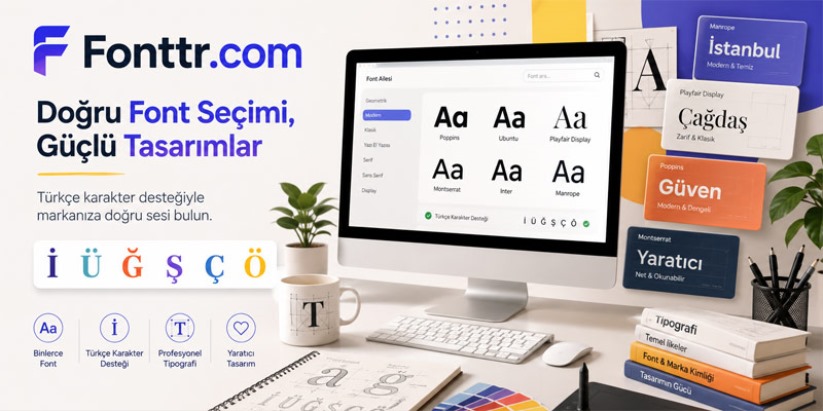
Dijital tasarımda kullanılan yazı tipi, bir görselin ya da web sayfasının ilk bakışta nasıl algılanacağını doğrudan etkiler.
Bir başlığın güçlü görünmesi, bir afişin dikkat çekmesi, sosyal medya görselinin okunabilir olması ya da bir logo çalışmasının akılda kalması çoğu zaman doğru font seçimiyle başlar. Özellikle Türkçe içerik üreten tasarımcılar, içerik üreticileri ve web sitesi sahipleri için font seçerken yalnızca estetik görünüm yeterli değildir. Seçilen yazı tipinin Türkçe karakterleri doğru göstermesi de büyük önem taşır.
Bir font görsel olarak ne kadar güzel olursa olsun, 'ğ, ü, ş, İ, ö, ç' gibi Türkçe karakterleri düzgün desteklemiyorsa profesyonel bir kullanım için sorun oluşturabilir. Bu nedenle Türkçe karakter desteği bulunan yazı tiplerini tercih etmek, hem okunabilirlik hem de marka algısı açısından daha sağlıklı bir seçimdir.
Font Seçimi Tasarımın Diline Yön Verir
Her yazı tipinin kendine ait bir karakteri vardır. Sans serif fontlar daha sade, modern ve okunabilir bir yapı sunarken; serif fontlar daha klasik, ciddi ve kurumsal bir görünüm sağlayabilir. El yazısı fontları daha samimi ve kişisel bir hava oluştururken, kaligrafi tarzındaki yazı tipleri davetiye, özel gün tasarımları, butik marka çalışmaları ve estetik görseller için tercih edilebilir.
Başlık fontları ise özellikle dikkat çekmesi gereken alanlarda kullanılır. Bir haber sitesi görselinde, YouTube kapak tasarımında, blog başlığında veya kampanya afişinde güçlü bir başlık fontu seçmek, içeriğin fark edilmesini kolaylaştırır. Fakat burada dikkat edilmesi gereken nokta, fontun yalnızca dikkat çekici olması değil, aynı zamanda rahat okunabilir olmasıdır.
Türkçe İçeriklerde Uyumlu Font Kullanımı
Türkçe içeriklerde en sık karşılaşılan problemlerden biri, bazı fontların Türkçe karakterleri eksik ya da hatalı göstermesidir. Bu durum tasarımın bütünlüğünü bozabilir. Örneğin bir sosyal medya görselinde 'ışık', 'güçlü', 'çalışma' veya 'özgün' gibi kelimelerdeki karakterler yanlış görünüyorsa, hazırlanan tasarım amatör bir izlenim bırakabilir.
Bu yüzden font indirirken ön izleme alanında mutlaka Türkçe karakterler denenmelidir. 'İÜĞŞÇÖ ıüğşçö' gibi karakterleri test etmek, fontun Türkçe kullanıma uygun olup olmadığını hızlıca anlamayı sağlar. Bu basit kontrol, özellikle web tasarımı, logo çalışmaları, reklam görselleri, blog kapakları ve sosyal medya içerikleri hazırlayanlar için oldukça faydalıdır.
Farklı Kategoriler Farklı Kullanım Alanları Sunar
Font ararken ihtiyaç duyulan tasarım türüne göre kategori seçmek zaman kazandırır. Örneğin modern bir teknoloji sitesi için sade ve net sans serif yazı tipleri daha uygun olabilir. Moda, fotoğrafçılık ya da kişisel blog tasarımlarında daha estetik ve zarif fontlar tercih edilebilir. Retro ve vintage tarzı fontlar nostaljik bir görünüm oluştururken, graffiti veya çizgi film tarzı fontlar daha eğlenceli ve genç bir kitleye hitap eden çalışmalarda kullanılabilir.
E-ticaret bannerları, haber sitesi görselleri, kampanya başlıkları ve reklam tasarımlarında ise düz, kalın ve okunabilir fontlar daha iyi sonuç verir. Çünkü kullanıcı çoğu zaman görsele yalnızca birkaç saniye bakar. Bu kısa sürede mesajın net biçimde anlaşılması gerekir.
Özellikle marka logosu, ürün ambalajı, reklam kampanyası, web sitesi tasarımı veya ticari sosyal medya görsellerinde kullanılacak fontlar için lisans detaylarını incelemek önemlidir. Bu kontrol, ileride yaşanabilecek telif ve kullanım hakkı sorunlarının önüne geçebilir.
Tasarımda Okunabilirlik Estetikten Önce Gelir
Görsel olarak çok dikkat çekici bir font, her zaman doğru seçim olmayabilir. Uzun metinlerde fazla süslü ya da karmaşık yazı tipleri okumayı zorlaştırabilir. Bu nedenle başlık, alt başlık ve gövde metni için farklı font dengesi kurulmalıdır.
Başlıklarda daha karakterli ve dikkat çekici fontlar kullanılabilir. Ancak açıklama metinlerinde sade, gözü yormayan ve ekran üzerinde rahat okunan yazı tipleri tercih edilmelidir. Web tasarımında bu denge, kullanıcı deneyimini doğrudan etkiler.
Doğru Font Daha Güçlü Bir Görsel Kimlik Oluşturur
Bir web sitesi, sosyal medya hesabı ya da marka için kullanılan yazı tipi zamanla görsel kimliğin bir parçası haline gelir. Sürekli farklı fontlar kullanmak, tasarım dilinde dağınık bir görüntü oluşturabilir. Bunun yerine birkaç ana font belirleyip bu yazı tiplerini düzenli kullanmak daha profesyonel bir görünüm sağlar.
Font seçimi yapılırken hedef kitle, içerik türü, sektör ve kullanılacak platform birlikte düşünülmelidir. Eğlenceli bir içerik sitesiyle kurumsal bir danışmanlık firmasının aynı yazı tipini kullanması beklenmez. Her projenin dili farklıdır ve doğru font bu dili güçlendirir.